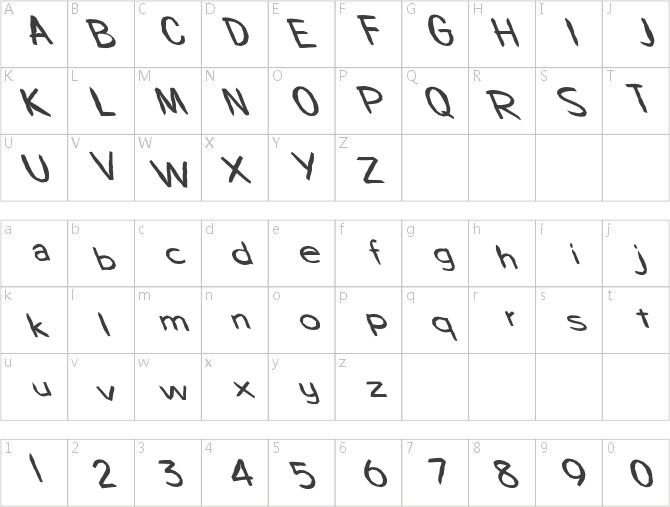
FZ HAND 7 MANGLED LEFTY 详情页
FZ HAND 7 MANGLED LEFTY
FZ HAND 7 MANGLED LEFTY介绍
FZ HAND 7 MANGLED LEFTY字体字库是一款让人赏心悦目、百看不厌的英文字体,适合各类广告和产品包装设计应用,字体大小0.06MB,格式为ttf字体,上传用户是FaYu,作者/版权方为未知